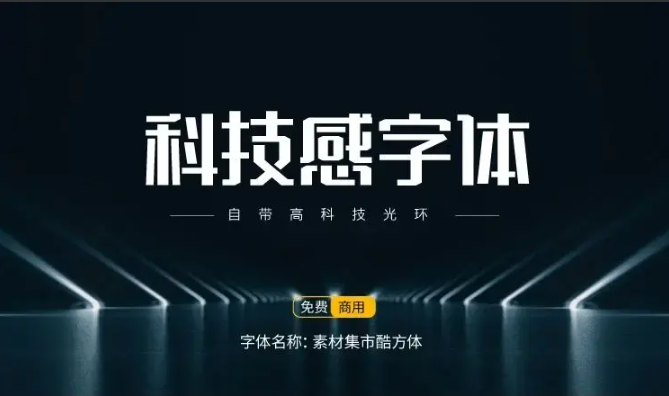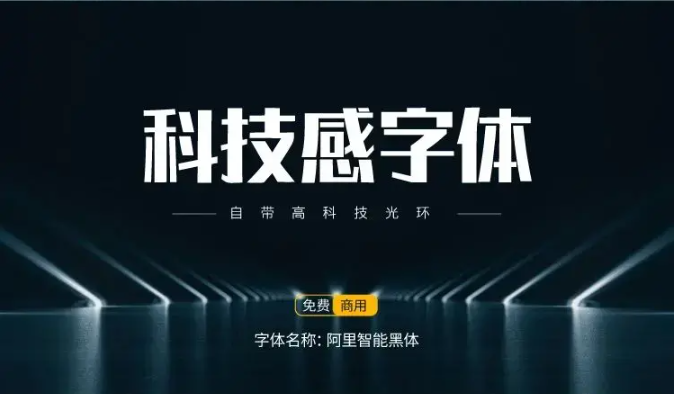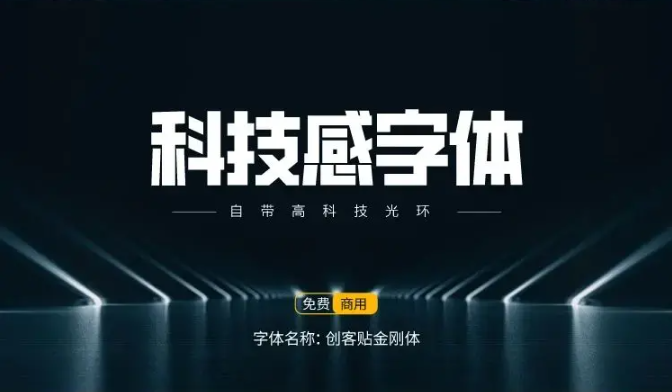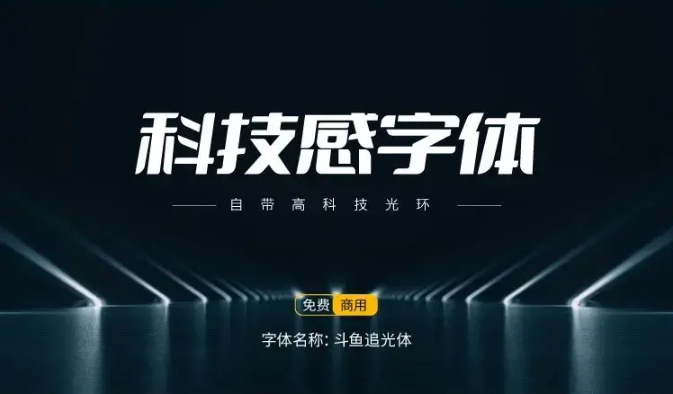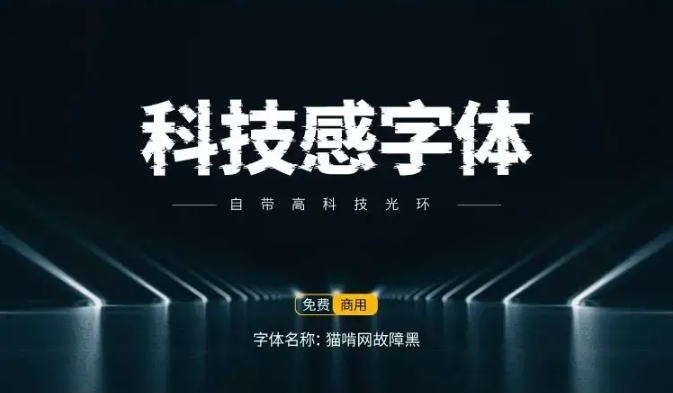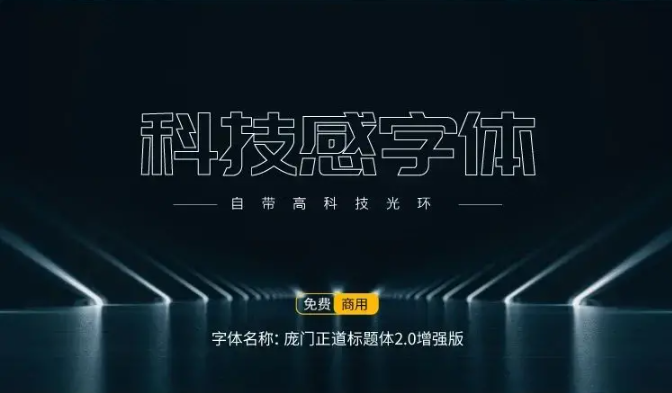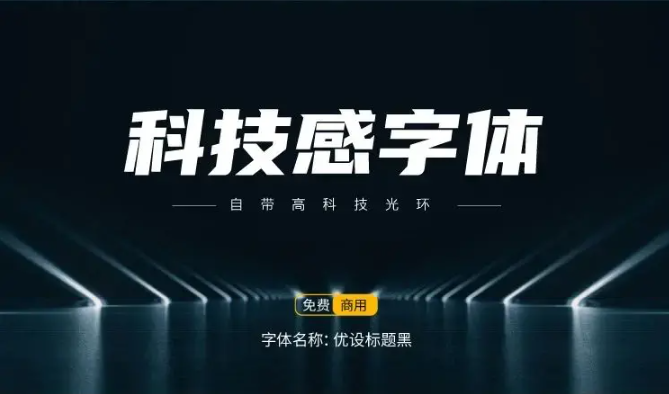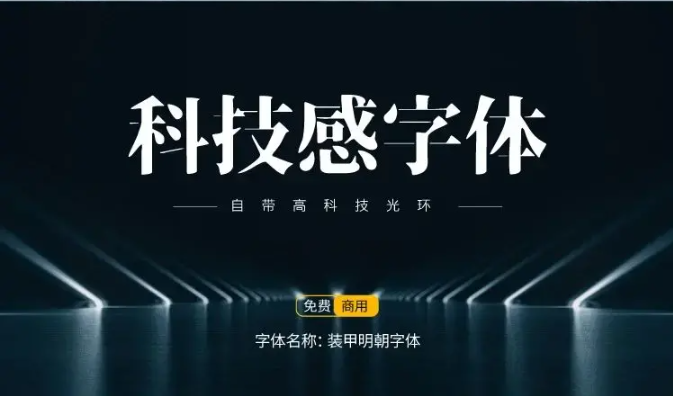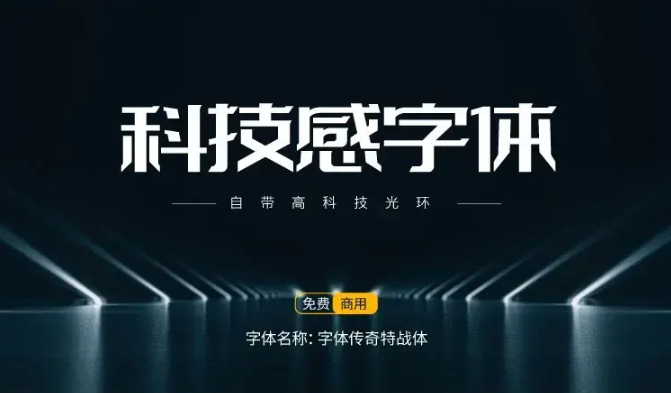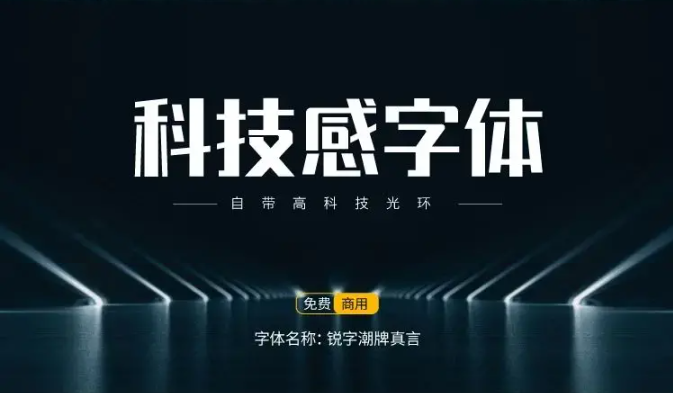
15款科技感字体推荐:让设计未来感爆棚的免费商用字体合集
在数字化时代,科技感设计已成为品牌传播的核心诉求。本文精选15款兼具未来感与实用性的免费商用字体,涵盖可变字体、AI生成字体、故障风格等前沿设计,助力设计师打造极具冲击力的视觉作品。
1. 锐字潮牌可变真言2.0简
特点:首款支持可变字体技术的中文黑体,6档字重自由调节,横竖笔画粗细对比可动态调整。
适用场景:网页适配、动态海报、品牌VI系统,解决多设备显示兼容问题。
亮点:中性笔画设计搭配呼吸感留白,兼具现代感与易读性。
2. 阿里妈妈数黑体(Alimama ShuHeiTi_Bold)
特点:阿里妈妈团队研发,字型饱满、布白现代,落笔厚实简练。
适用场景:电商广告、品牌主视觉、促销物料,AI人机协同设计典范。
亮点:7025字符覆盖GB2312标准,兼顾通用性与时尚感。
3. 阿里汉仪智能黑体
特点:首款AI生成字体,笔画融入手写韵律,刚中带柔。
适用场景:阿里平台专属,电商标题、直播封面设计。
亮点:通过计算能力自学生成,平衡效率与美观。
4. 创客贴金刚体
特点:极简无衬线设计,1:1字型比例,笔画粗度150pt。
适用场景:商业海报、包装设计、品牌宣言标题。
亮点:6763个简体字+符号,满足基础排版需求。
5. 斗鱼追光体2.0
特点:倾斜粗体设计,笔画充满活力,配套英文美观。
适用场景:综艺标题、游戏海报、影视包装。
6. 金山云技术体
特点:无衬线硬朗风格,12度倾斜笔画衔接。
适用场景:科技产品海报、技术文档标题、数据可视化图表。
亮点:历时四年打磨,单字重设计专注标题场景。
7. 联盟起艺卢帅正锐黑体
特点:横向笔画细斜角设计,打破粗黑体沉闷感。
适用场景:活动主视觉、展览海报、运动品牌宣传。
亮点:8000+字符覆盖,学员与设计师共创成果。
8. 猫啃网故障黑
特点:基于思源黑体改造,故障艺术风格,程序自动生成。
适用场景:赛博朋克主题、数字艺术、故障风视频包装。
9. 庞门正道标题体2.0增强版
特点:高辨识度粗黑体,新增6230个字符。
适用场景:自媒体封面、电商促销标语、线下展板。
10. 庞门正道细线体
特点:纤细优雅无衬线,适合小字号排版。
适用场景:高端品牌文案、时尚杂志标题、UI界面设计。
11. 素材集市酷方体
特点:方正刚劲,笔画如刀刻,力量感十足。
适用场景:工业产品广告、健身品牌视觉、军事主题设计。
12. 优设标题黑
特点:高对比度笔画,视觉冲击力强。
适用场景:活动主标题、电影海报、游戏界面。
亮点:优设网经典之作,适配多种设计软件。
13. 站酷高端黑体
特点:简约现代,笔画流畅自然。
适用场景:品牌LOGO、名片设计、高端产品包装。
亮点:站酷设计师力荐,平衡专业感与亲和力。
14. 装甲明朝体
特点:思源宋体改造,横线极细如刻刀,军事硬朗风。
适用场景:越野车广告、战术装备品牌、男性向产品设计。
亮点:日系开源字体,支持繁简与日文。
15. 字体传奇特战体
特点:横细竖粗,尖角修饰,充满力量感。
适用场景:品牌标识、运动赛事海报、科技发布会主视觉。
亮点:标准版与斜体双版本,GB2312全字符覆盖。